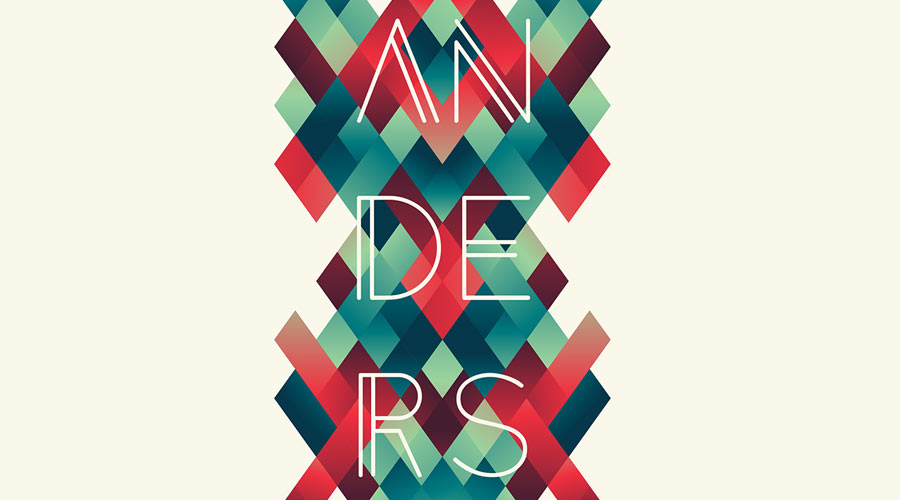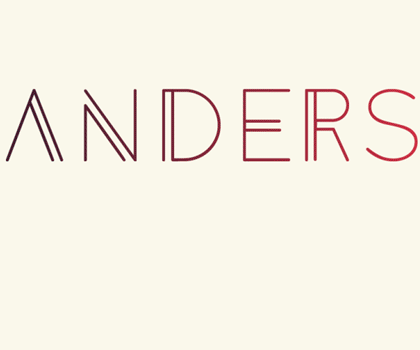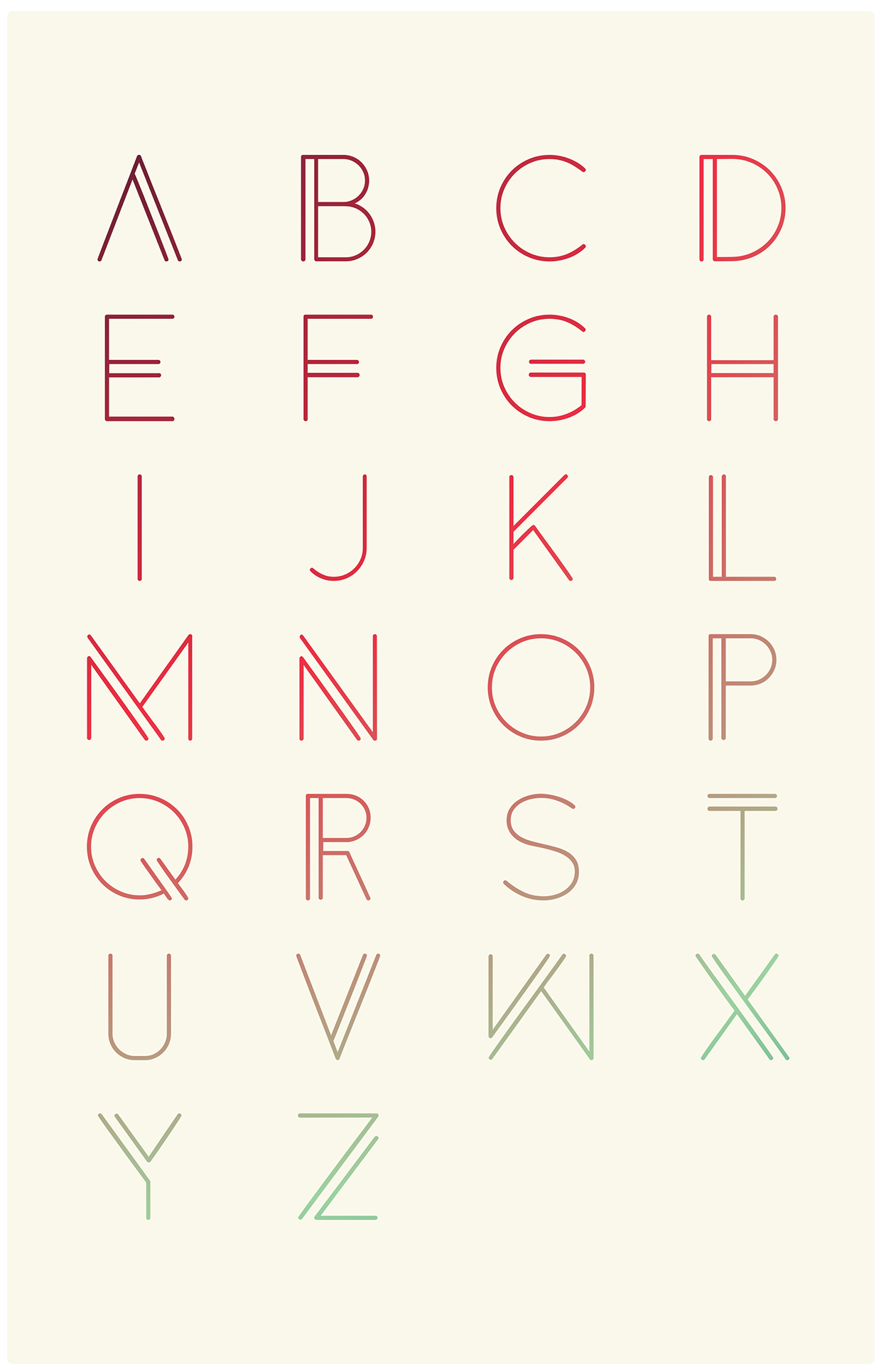
Hoy vamos con un proyecto experimental que decidió crear el diseñador inglés Tom Anders Watkins. Anders(como su apellido) es una fuente tipográfica sans serif de influencias modernas y minimalistas.